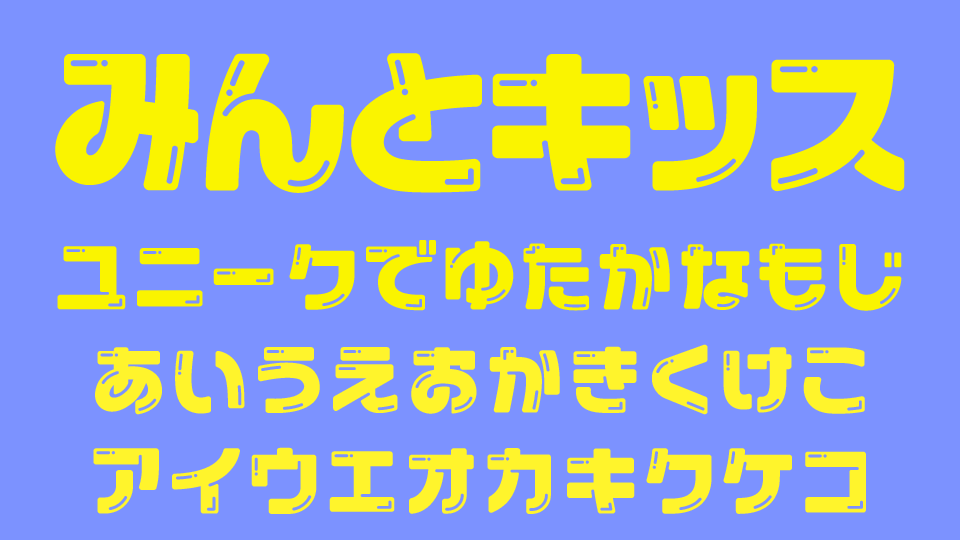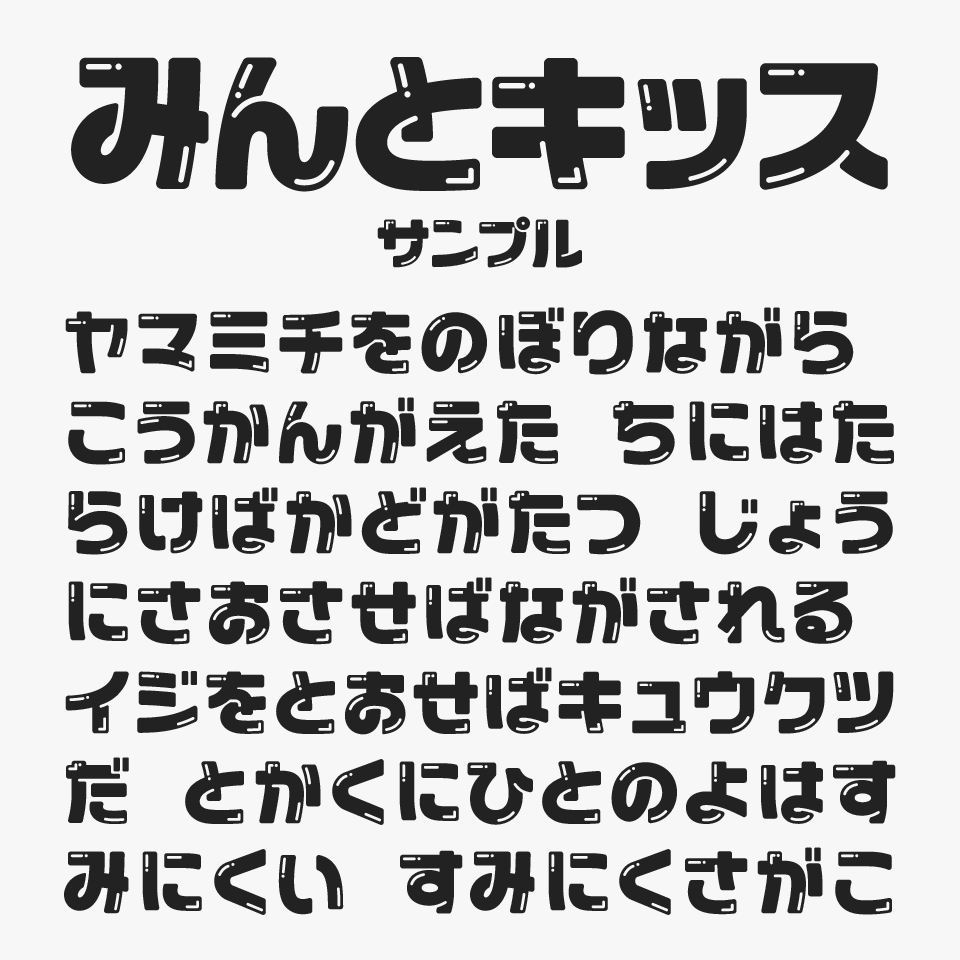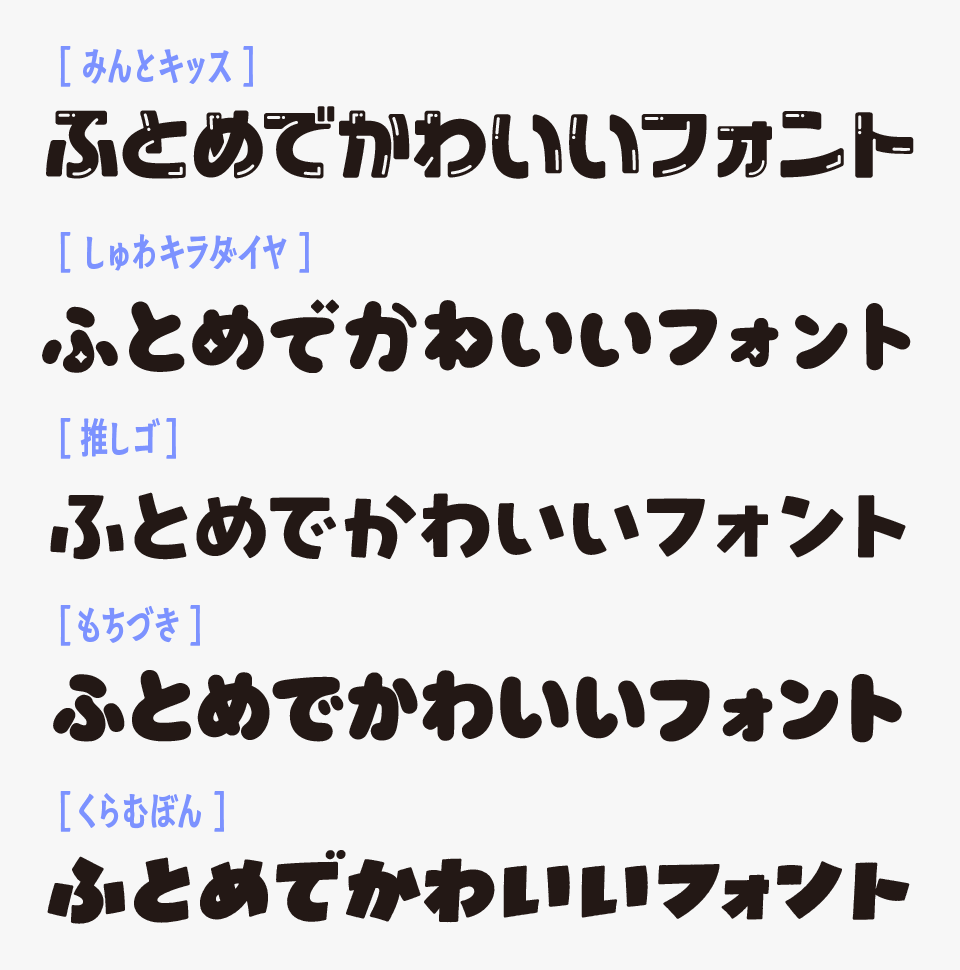
みんとキッス
みんとキッスフォントは、80年代のアイドル文化やポップカルチャーを思わせる、レトロでキュートなデザインフォントです。
文字には大胆な切り込みや光沢表現が取り入れられており、ポップな印象を持ちながらも、どこかラブコメ作品のタイトルのような甘酸っぱさや、ときめきを感じられるところも魅力です。
一文字ごとの存在感が強いため、タイトルやロゴ、サムネイルなどで使用すると抜群のインパクトを発揮します。最近では「うちわ文字」のフォントとしても人気あるフォントの1つです。
レトロポップなデザインやアイドル風ビジュアル、80〜90年代をイメージしたコンテンツとも相性が良く、見ているだけで楽しい気分になれるフォントとなっています。
大きい文字サイズで使用すると、光沢の質感がくっきりと表現されるので、タイトルやロゴに使うことがおすすめです。
色合いによっても印象が変わってくる本当に可愛らしいフォントです。
みんとキッスフォントを、ほかの太めで可愛らしい雰囲気を持つフォントと比較してみると、ツルっと光っているような光沢感と、80年代アイドルやレトロポップカルチャーを感じさせる独特の世界観が特に魅力のフォントです。
比較フォントは、「しゅわキラダイヤ」「推しゴ」「もちづき」「くらむぼん」と使用していますが、どれも極太でふっくら可愛いフォントで推し活などで活躍しているフォントなので、ぜひあわせてチェックしてみてください。
収録文字は、ひらがな・カタカナ・一部記号が収録されています。
漢字は収録していないので、印象が似ている「かわいい日本語フリーフォント」などと組み合わせて使用してみても良いかと思います。